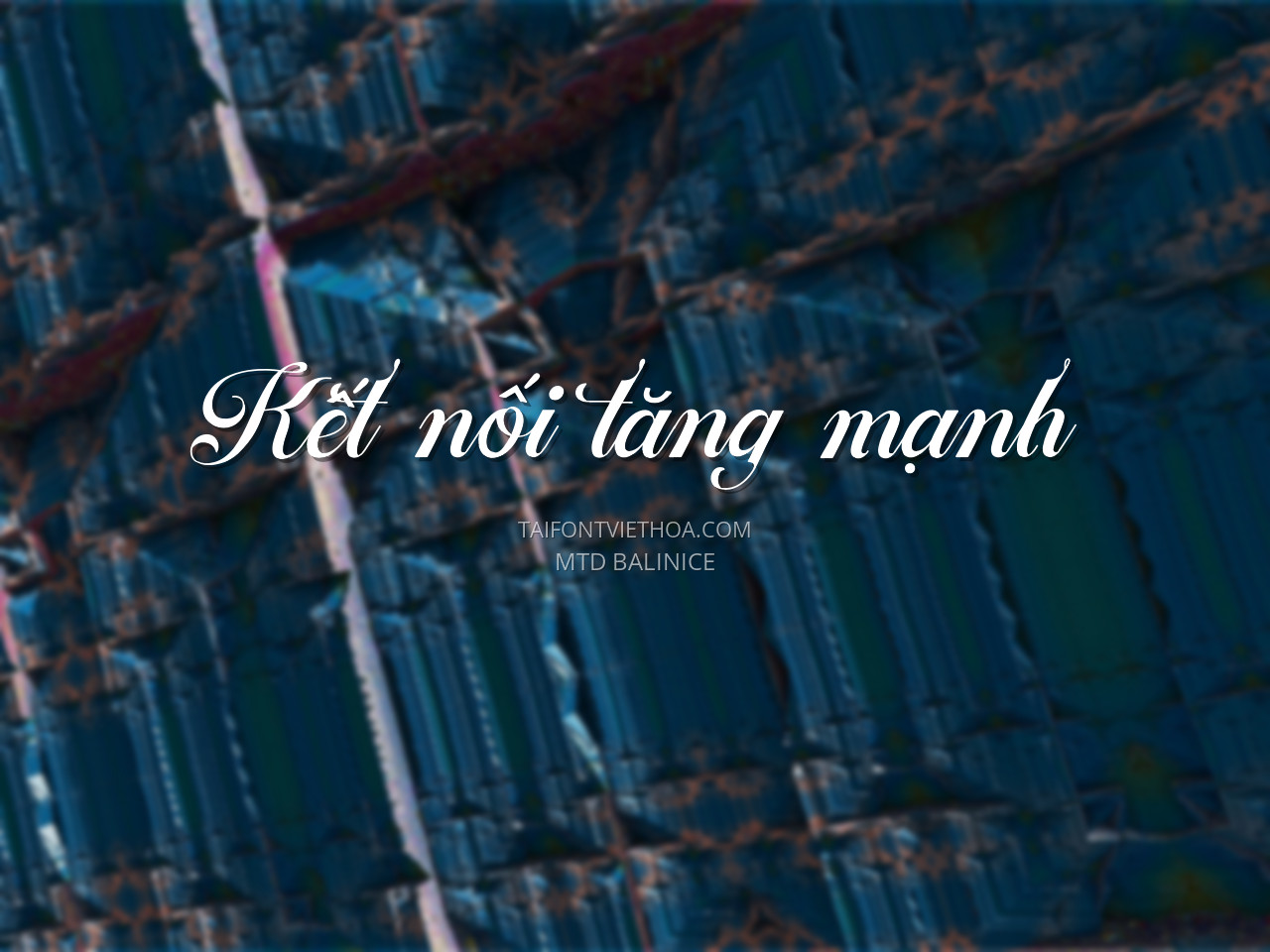
Font việt hóa MTD Balinice
Giới thiệu về font Balinice – Viết tay bay bổng và tinh tế cho thiết kế nữ tính hiện đại
Balinice là một kiểu chữ viết tay (handwritten script) mang phong cách hiện đại, mềm mại và đầy tinh tế. Font được thiết kế với các đường nét thanh mảnh, uốn lượn nhẹ nhàng, gợi cảm giác tự nhiên như nét bút tay của một nghệ sĩ. Balinice đặc biệt phù hợp với những thiết kế mang tính cá nhân hóa, tình cảm hoặc thương hiệu dành cho phái nữ như thiệp cưới, logo spa, bao bì mỹ phẩm hoặc sản phẩm thủ công. Font hỗ trợ bộ ký tự Latin mở rộng và nhiều ngôn ngữ phổ biến trên thế giới.
Phiên bản Việt hóa do Mộc Hạthực hiện đã được tối ưu hóa toàn bộ hệ thống dấu tiếng Việt, đảm bảo giữ nguyên tính thẩm mỹ, liền mạch và mượt mà trong từng nét chữ. Taifontviethoa.comđã chọn lọc và giới thiệu Balinice như một font chữ hoàn hảo cho các nhà thiết kế yêu thích sự nhẹ nhàng, thanh lịch và cảm xúc bay bổng trong các dự án sáng tạo tại Việt Nam.
Đặc điểm thiết kế mềm mại và ứng dụng thực tế của font Balinice
Balinice sở hữu cấu trúc chữ thanh mảnh, nghiêng nhẹ, với các ký tự nối liền uyển chuyển và nhiều ligatures giúp người dùng dễ dàng tạo nên những layout chữ sinh động, cá tính. Font còn đi kèm các ký tự thay thế (alternates) và swash trang trí giúp tăng tính nghệ thuật, rất lý tưởng trong thiết kế thiệp mời hoặc logo thương hiệu sáng tạo.
Font phù hợp với các thiết kế như: thiệp cưới, logo mỹ phẩm, bao bì organic, poster cảm xúc, blog cá nhân hoặc trích dẫn nghệ thuật. Ngành nghề lý tưởng gồm: ảnh cưới – thiệp cưới, spa – làm đẹp, sản phẩm handmade, mỹ phẩm thiên nhiên, thời trang nữ, thương hiệu cá nhân hoặc các dự án truyền thông mang tính cảm xúc và tinh tế.